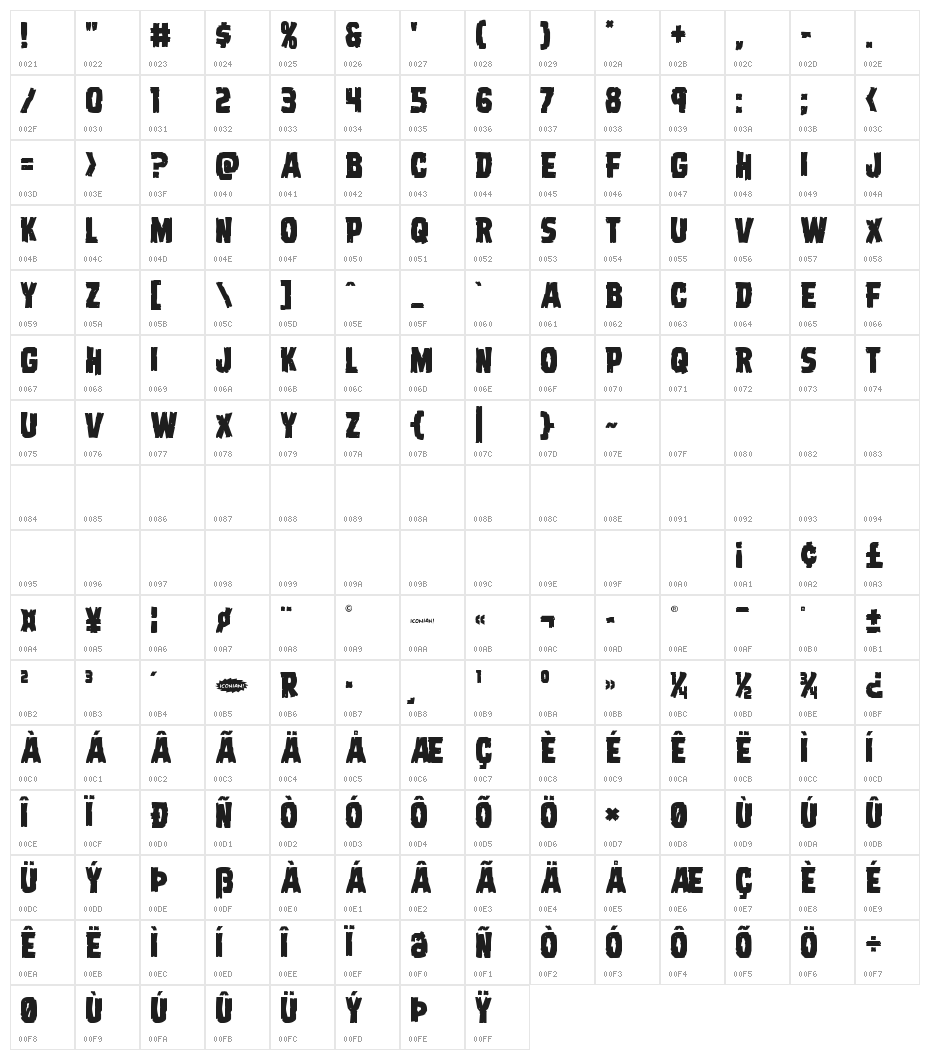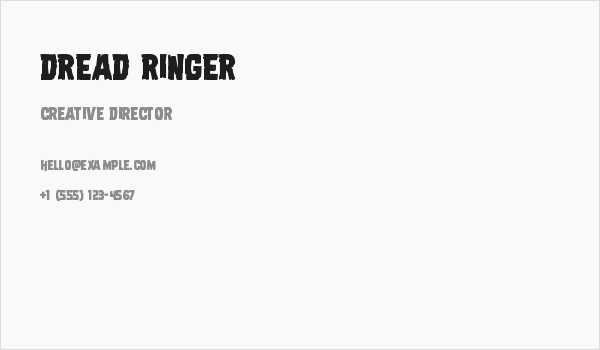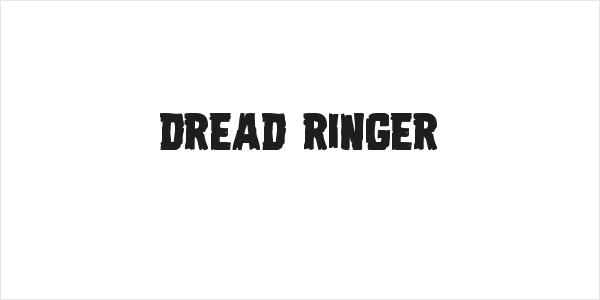
Dread Ringer Font
| Vorgeschlagene Projekte | Ideal for posters, album covers, branding for edgy products, or any design needing a strong, impactful look. |